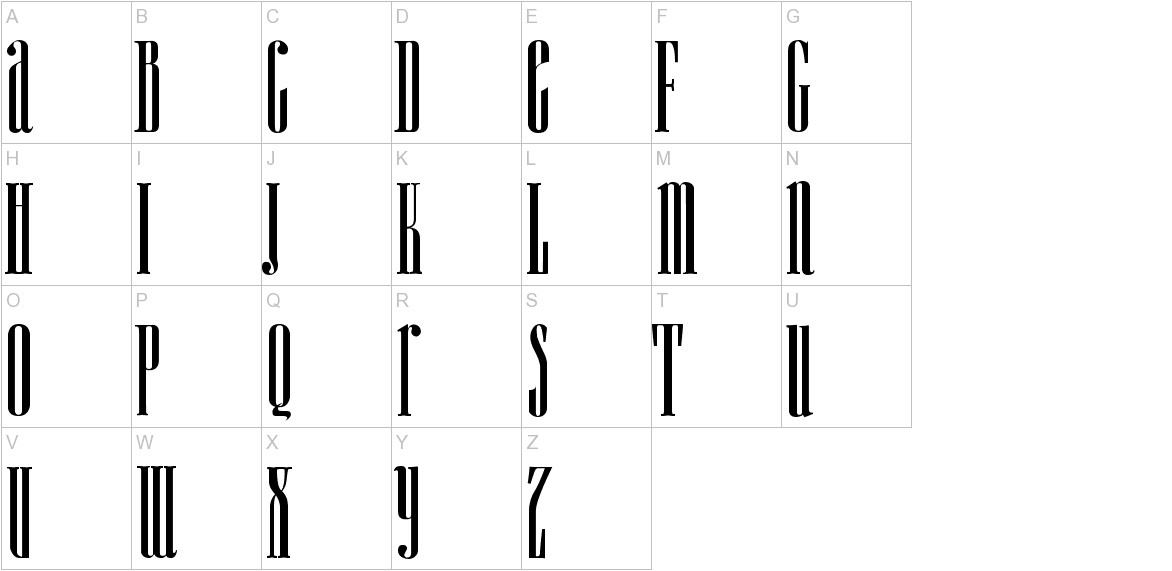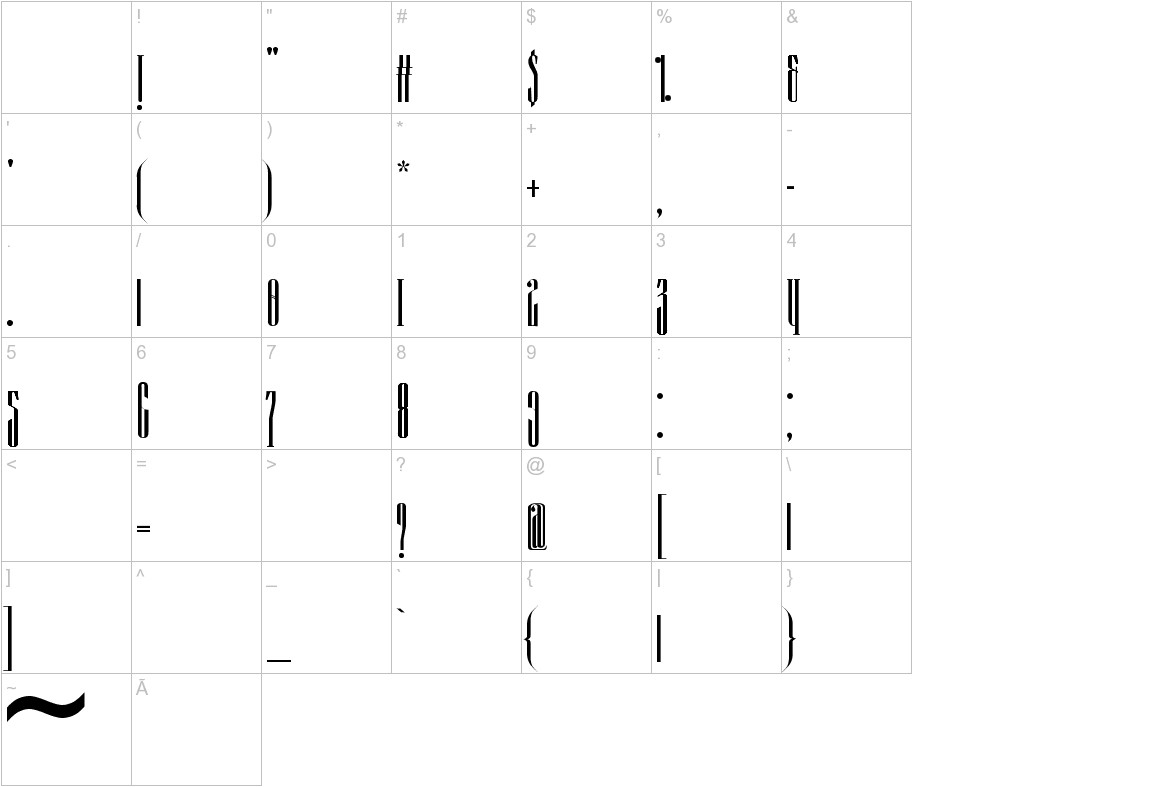
Quinn
Es una typo de display, no sirve para texto de corrido ni tiene ajustados los espaciados, aunque su uso va a criterio del diseñador.
Elegante y muy condensada, requiere que le den su espacio para que salga a ser vista :)